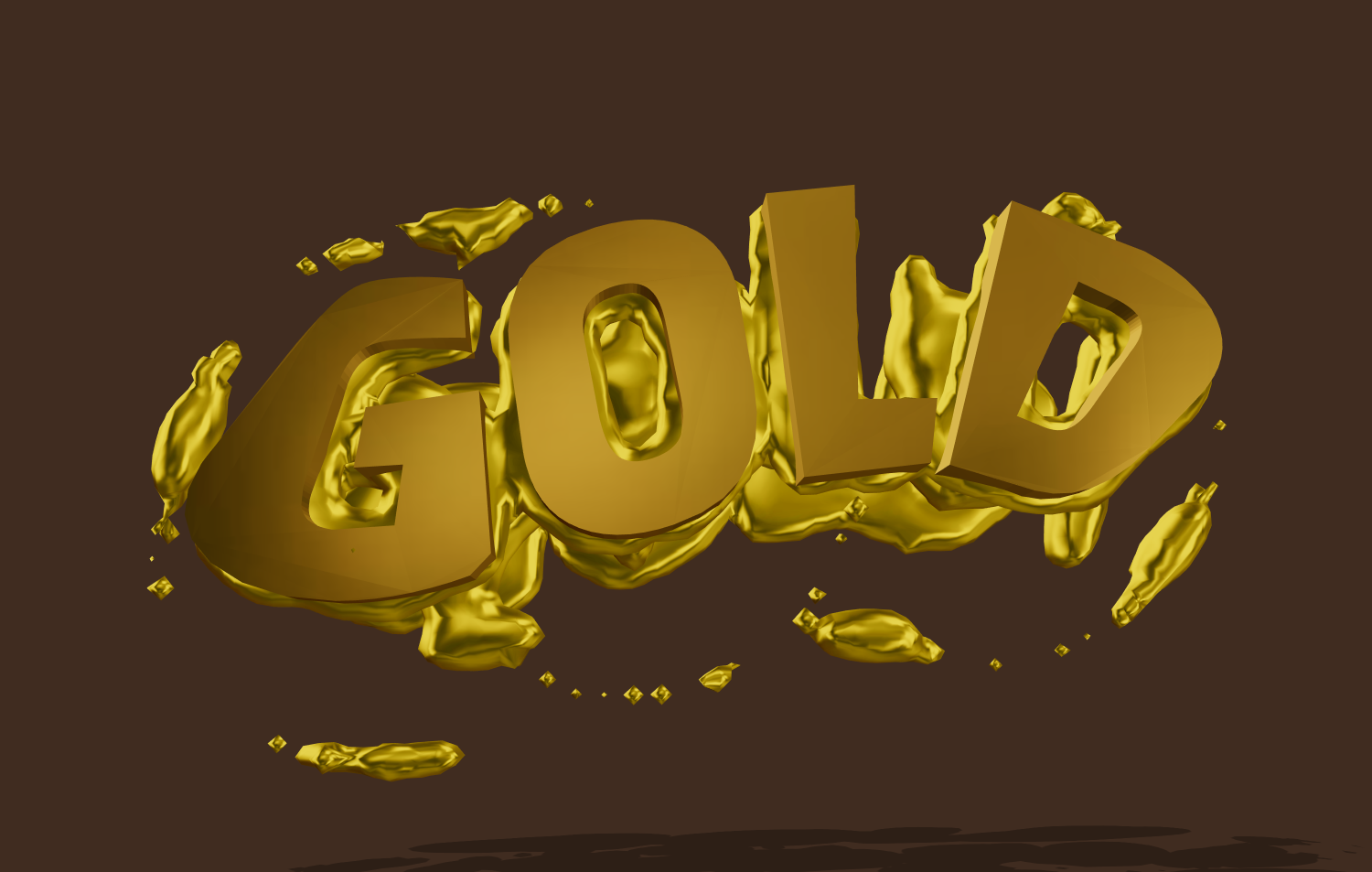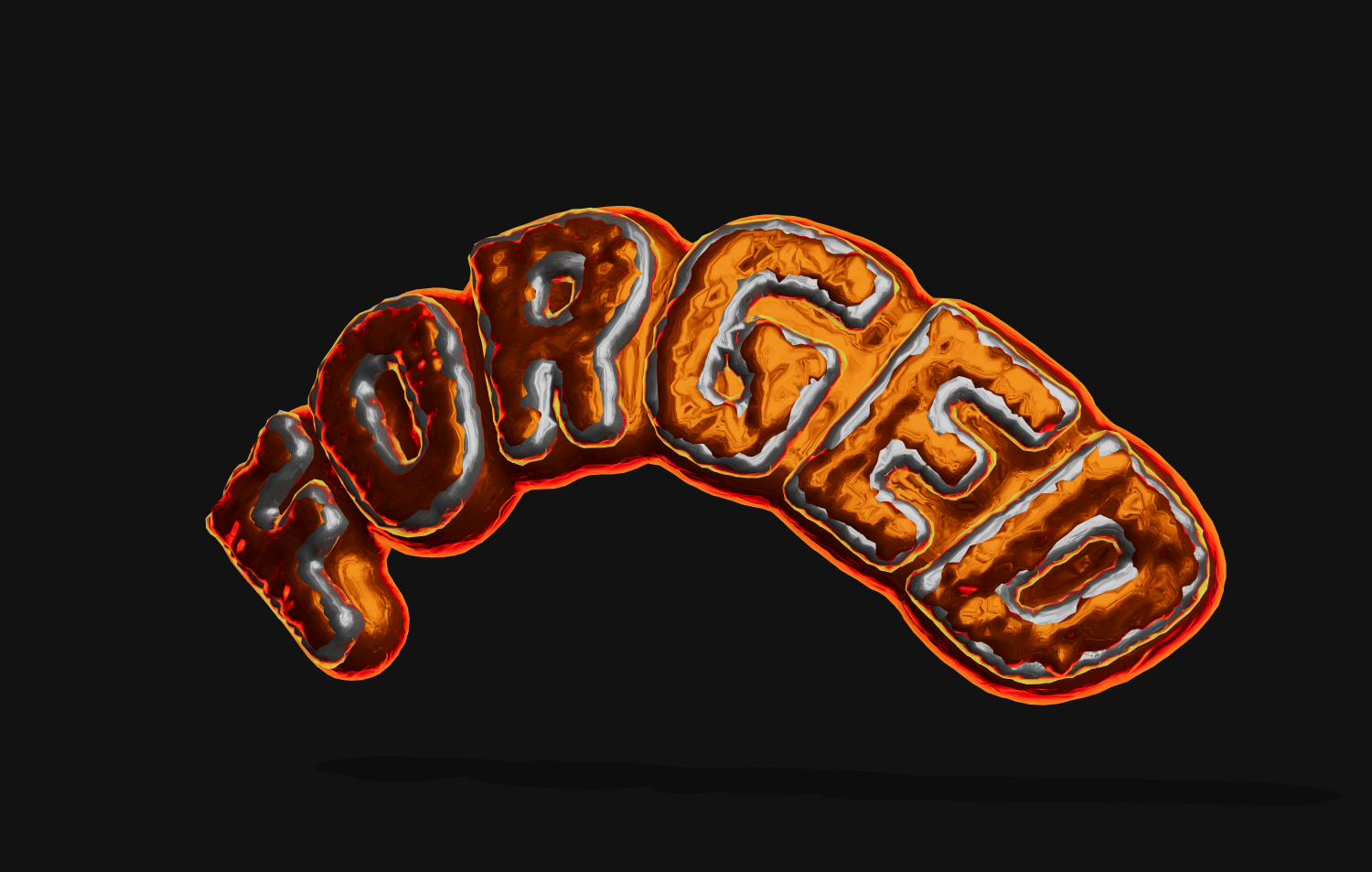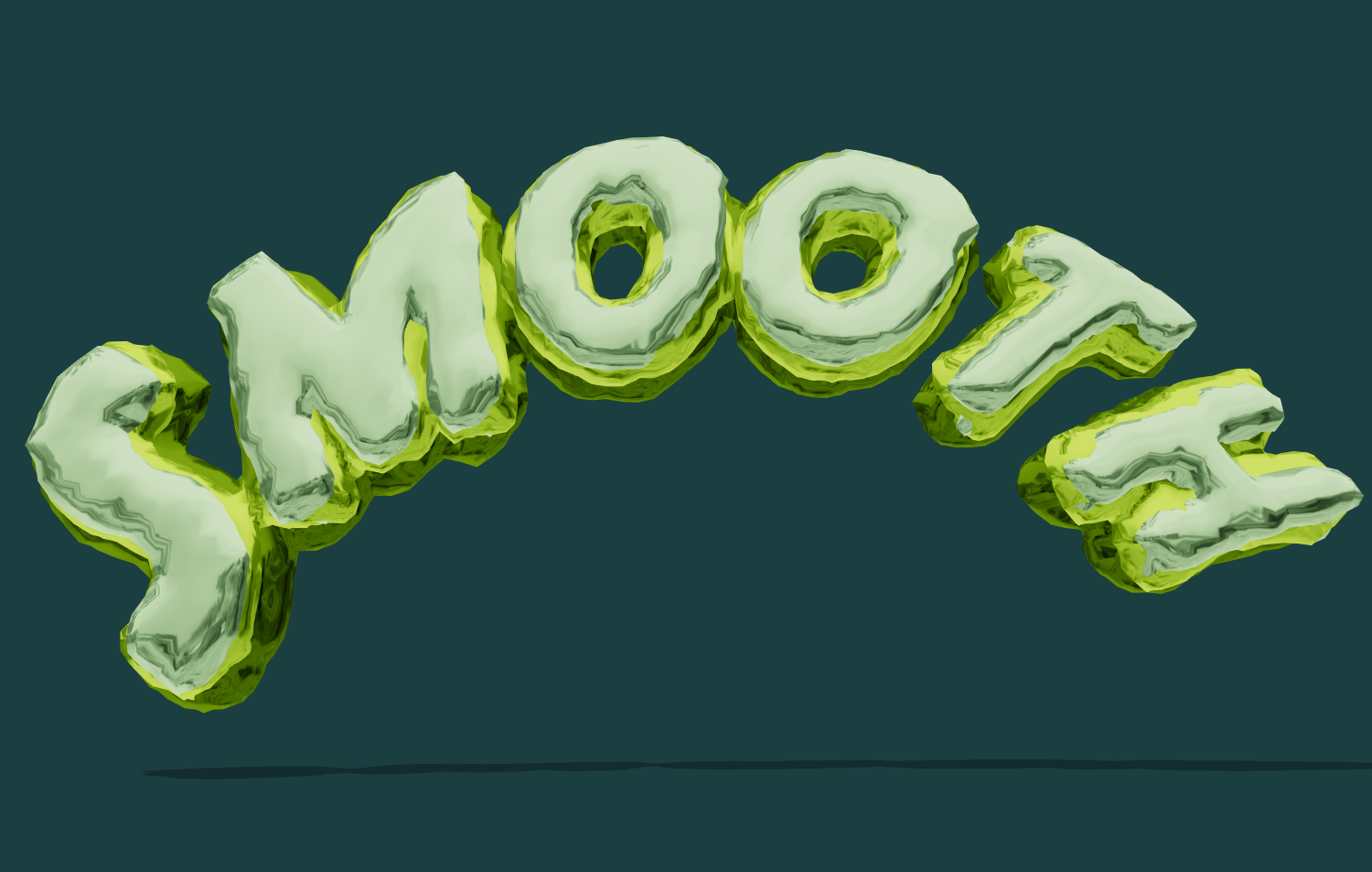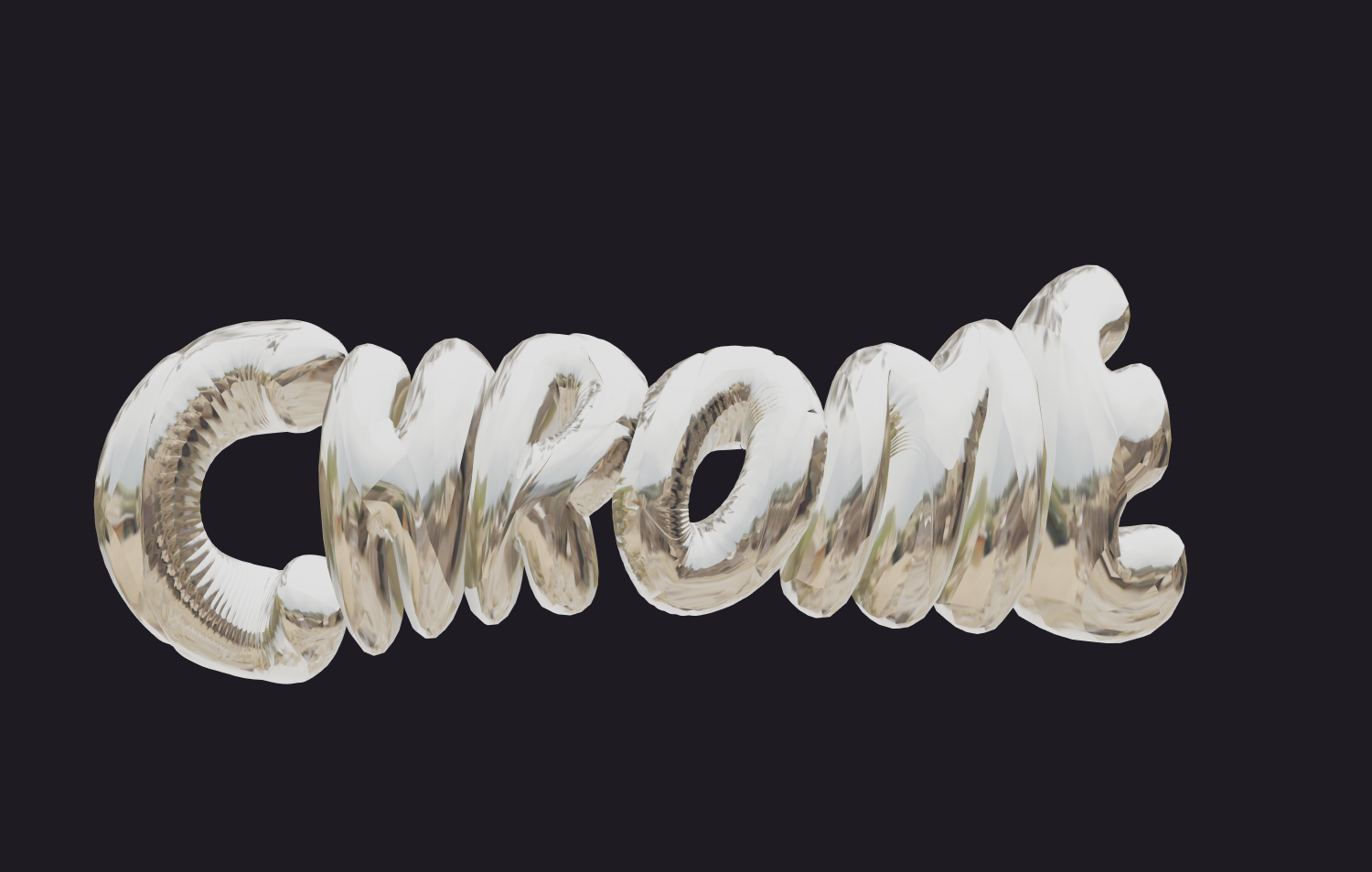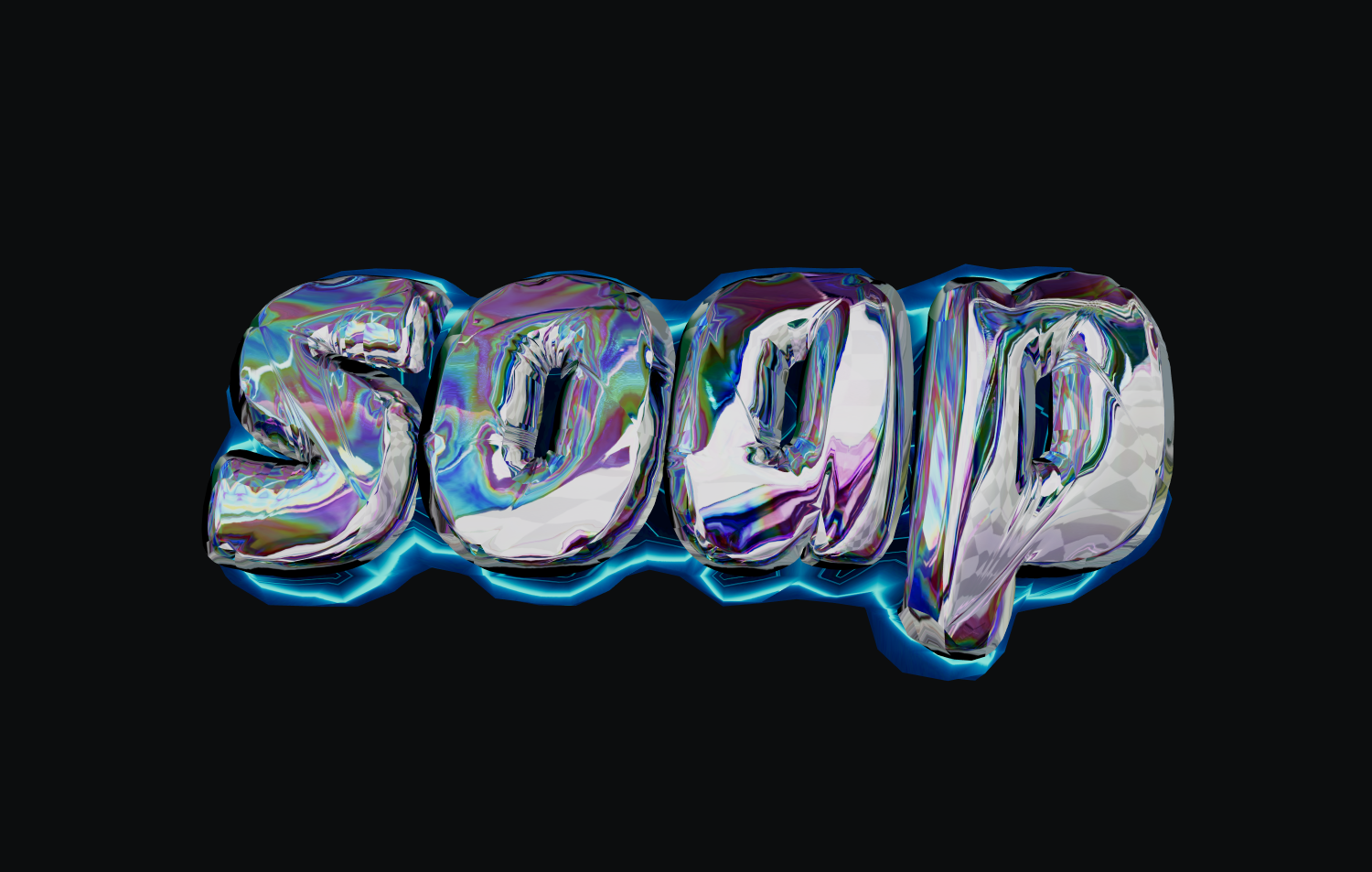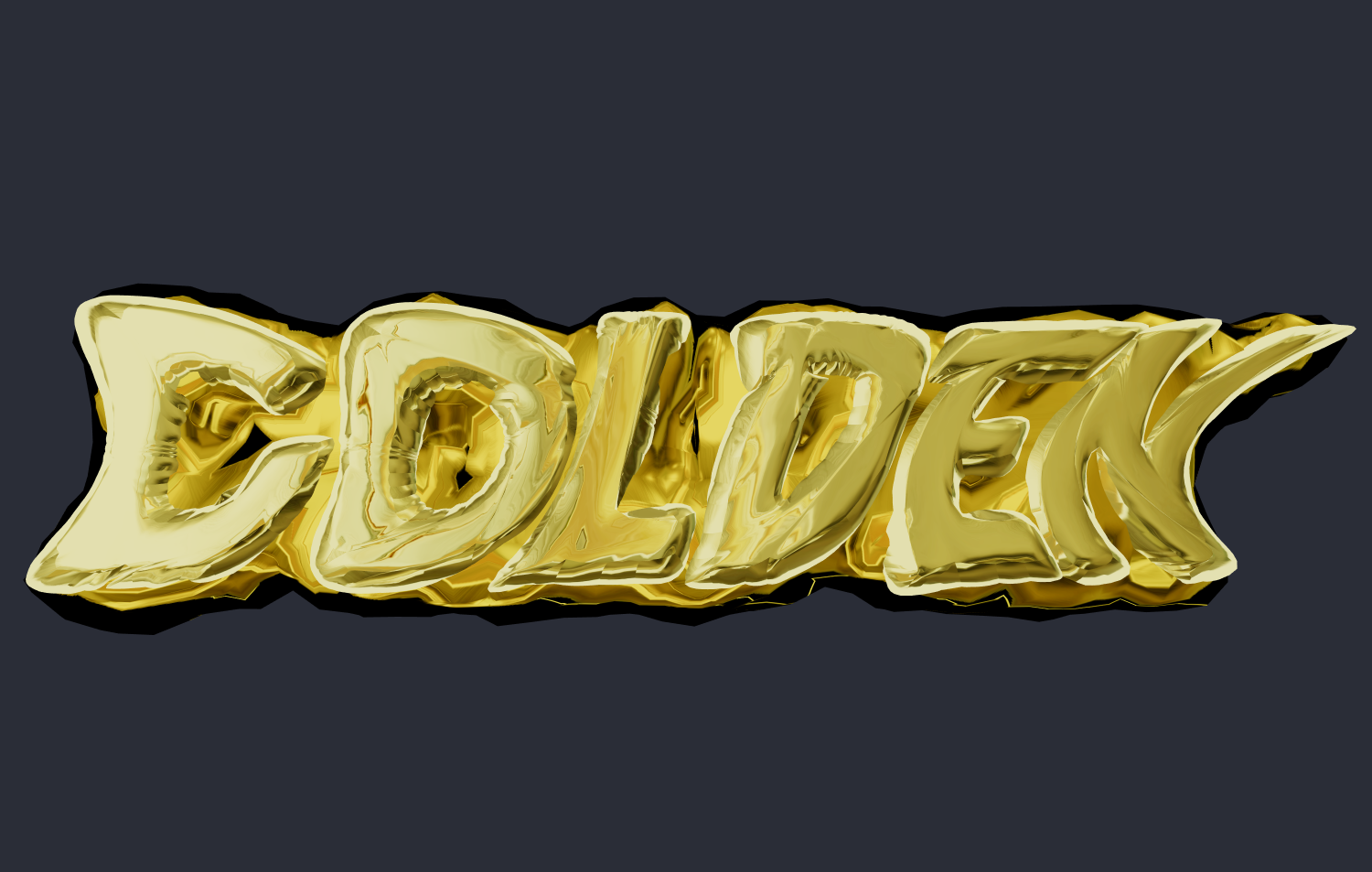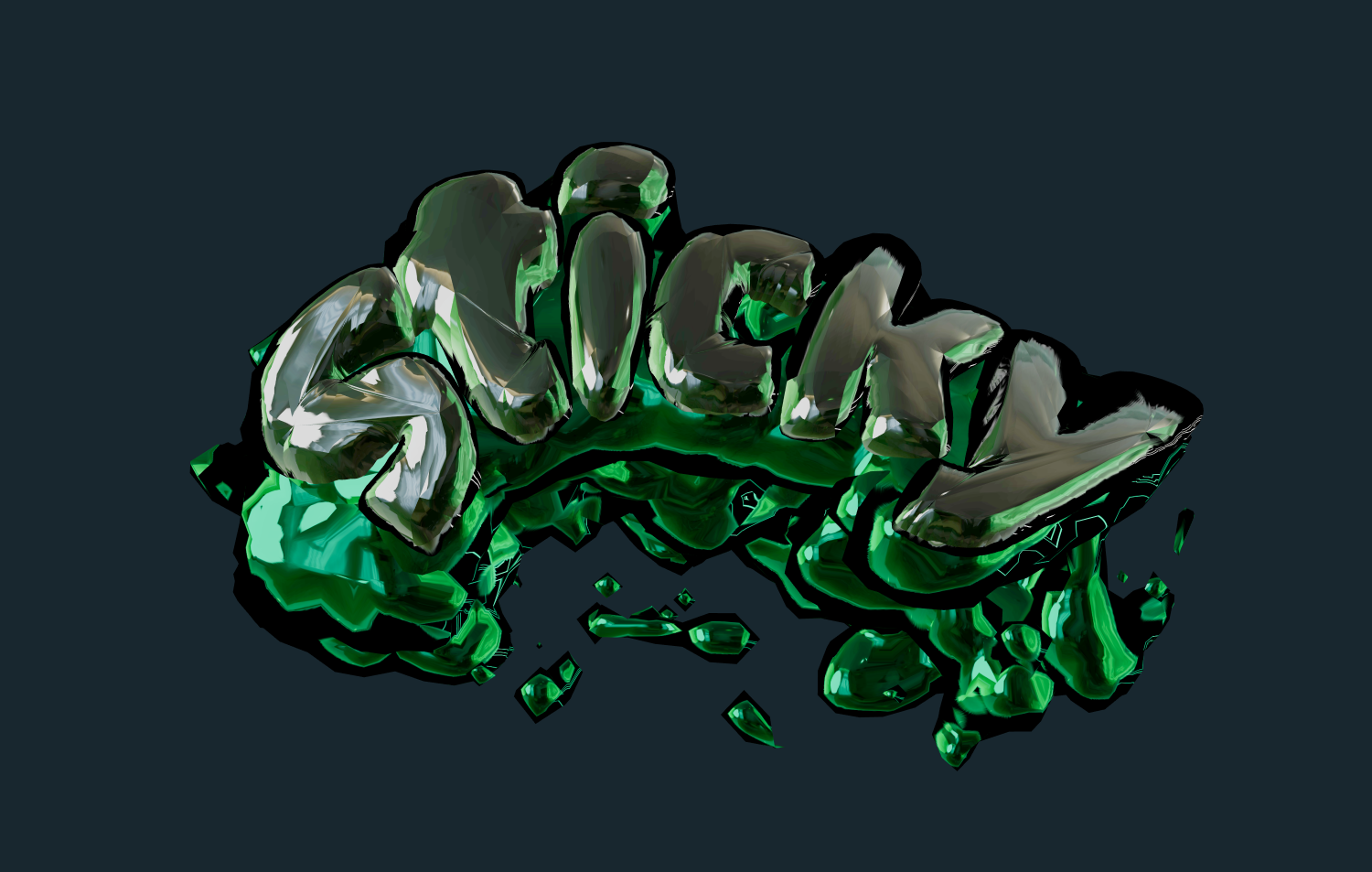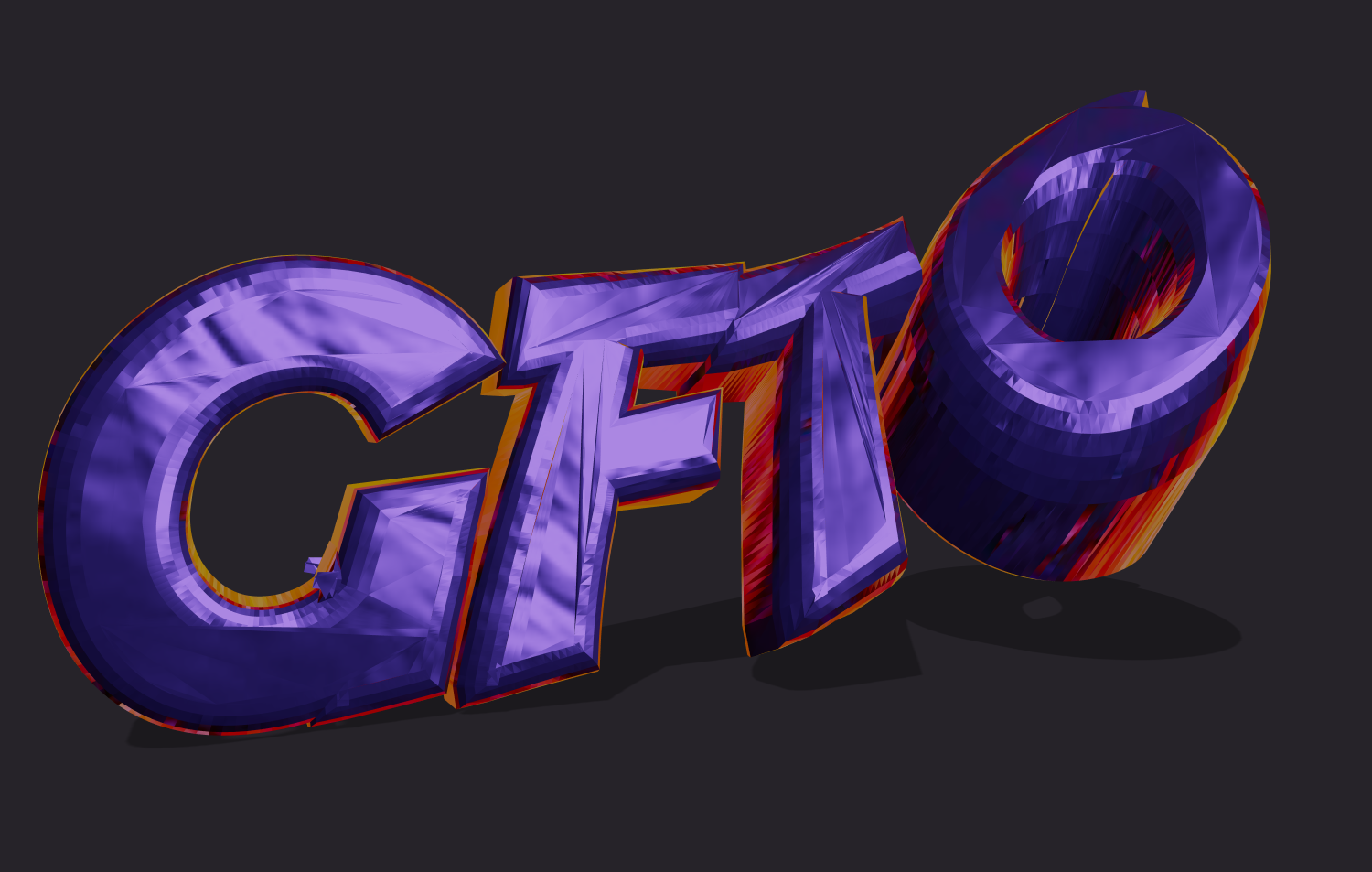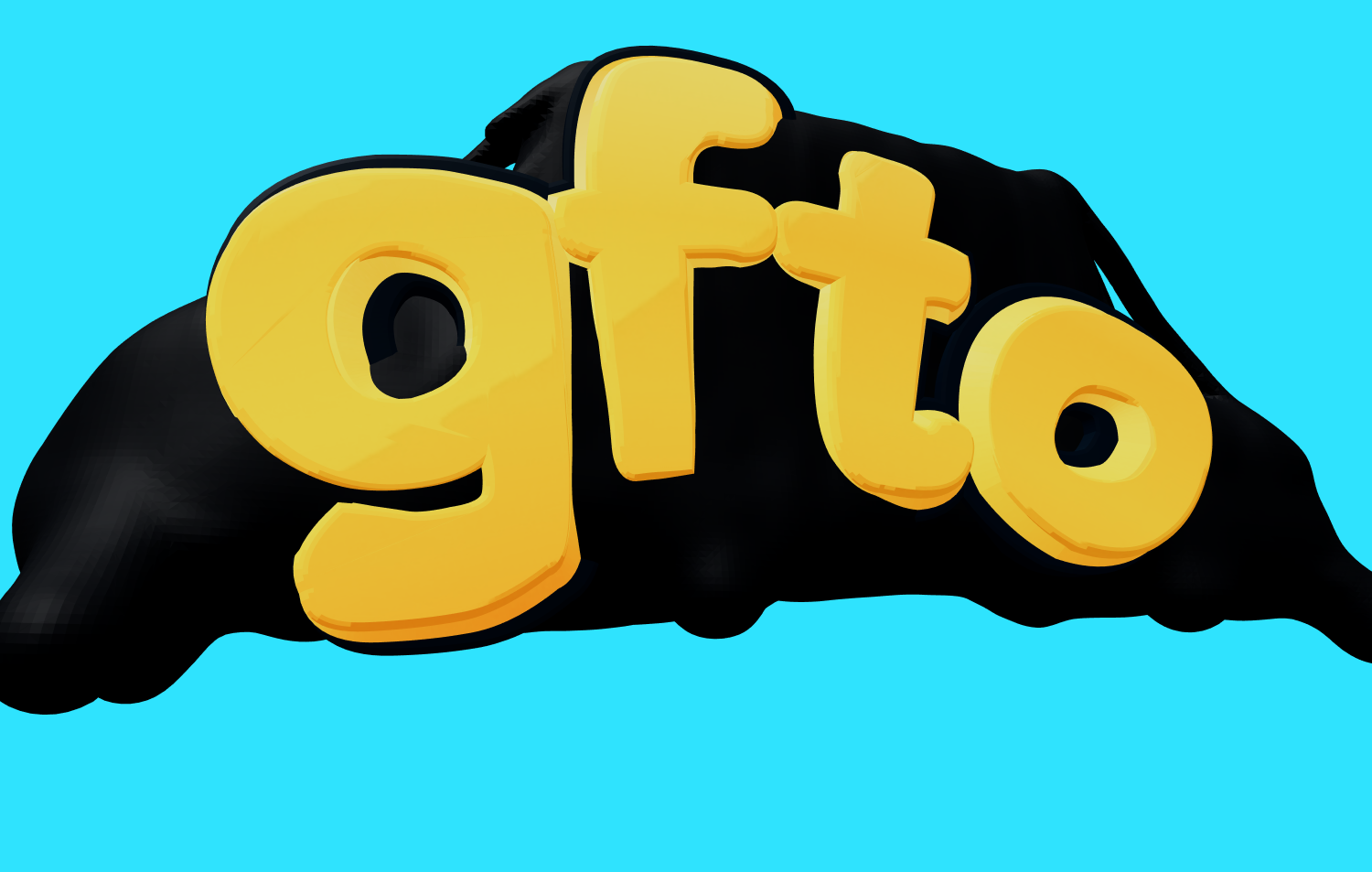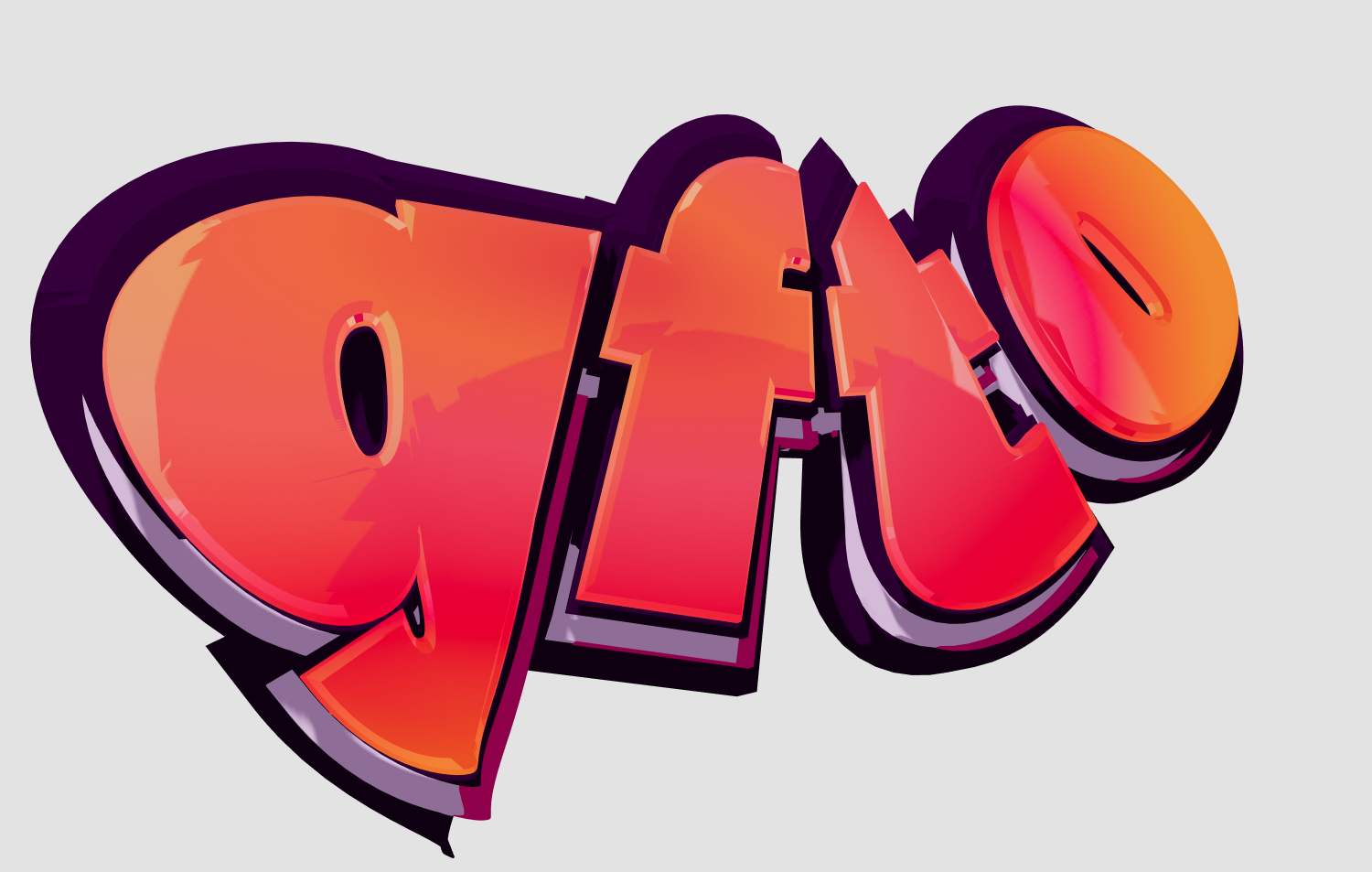
Генератор Красивых Шрифтов Онлайн
Напишите любой текст красивым шрифтом онлайн! Наш бесплатный сервис поможет вам создать красивую надпись для никнейма, социальных сетей, открыток или презентаций. Просто введите ваш текст и выберите один из сотен уникальных стилей.
Коллекция красивых шрифтов и стилей
Красивый шрифт в стиле ломкого стекла для создания красивой надписи
Красивый шрифт «Ломкое стекло»
Сделайте текст красивым шрифтом с эффектом трещин. Идеально для элегантных и хрупких надписей.
Красивая надпись голографическим шрифтом
Красивая надпись «Голография»
Футуристичный красивый шрифт с переливающимися цветами. Для технологичных и геймерских надписей.
Текст красивым шрифтом в стиле фиолетовой карамели
Текст красивым шрифтом «Карамель»
Сладкий и привлекательный дизайн для красивых надписей на тему еды, десертов и детских брендов.
Красивая надпись в стиле граффити
Красивый шрифт «Граффити Grape»
Сочный 3D граффити шрифт для создания динамичных и молодежных красивых надписей.
Сделать текст красивым хоррор-шрифтом
Красивый хоррор-шрифт «Scary»
Мрачный и яркий стиль, чтобы сделать текст по-настоящему пугающим. Идеально для Хэллоуина и игр.
Красивая надпись зеркальным хромированным шрифтом
Красивый шрифт «Зеркальный Хром»
Сделайте надпись с реалистичным зеркальным отражением. Премиальный и технологичный вид.
Красивый золотой шрифт в стиле пузыря
Золотой красивый шрифт «Bubble»
Объемные золотые буквы с глянцевой поверхностью для создания роскошной и красивой надписи.
Сделать текст красивым жидким шрифтом
Текст красивым шрифтом «Жидкость»
3D эффект с органической формой. Плавные линии и реалистичная жидкая текстура для вашей надписи.
Красивый шрифт в виде воздушного шара
Шрифт «Воздушный Шар»
Легкий и воздушный стиль для праздничных красивых надписей и поздравлений.
Красивая надпись в стиле жвачки
Красивая надпись «Жвачка»
Напишите текст липким и глянцевым шрифтом с эффектом плавления. Очень креативно!
Текст красивым шрифтом из потрескавшегося стекла
Шрифт «Стекло с трещинами»
Создайте красивую надпись из стекла с эффектом трещин. Хрупкая элегантность с элементами брутальности.
Красивый шрифт в виде выпечки и шоколада
Красивый шрифт «Выпечка»
Аппетитный дизайн для красивых надписей в кондитерских и пекарнях. Текст из теста и шоколада.
Сделать текст красивым зеленым шрифтом слизи
Красивый шрифт «Слизь»
Создайте яркий зеленый текст с глянцевой текстурой слизи для забавной и необычной надписи.
Красивая надпись кровавым шрифтом
Кровавый Текст
Сделайте надпись с эффектом брызг и потеков крови. Идеально для хоррор-тематики и триллеров.
Надпись красивым шрифтом жидкий хром и золото
Шрифт «Жидкий Хром и Золото»
Эффект расплавленного металла, который растекается по поверхности из золотых осколков. Роскошный и красивый стиль.
Сделать текст красивым шрифтом в виде смолы
Красивый шрифт «Черная Смола»
Текстовый эффект, имитирующий густую нефть или смолу с глянцевыми бликами и реалистичными брызгами.
Красивая надпись огненным металлическим шрифтом
Шрифт «Раскаленный Металл»
Огненный текстовый эффект кованого металла с трещинами. Мощь и сила в каждой букве вашей красивой надписи.
Написать текст красивым золотым шрифтом с брызгами
Текст «Жидкое Золото»
Создайте красивую надпись из расплавленного жидкого золота с динамичными брызгами.
Футуристичный красивый шрифт с ячейками
Красивый шрифт «Решетка»
Футуристичный текстовый эффект с ячеистой структурой. Отлично подходит для тем технологий и науки.
Написать текст красивым шрифтом в виде мыльной пены